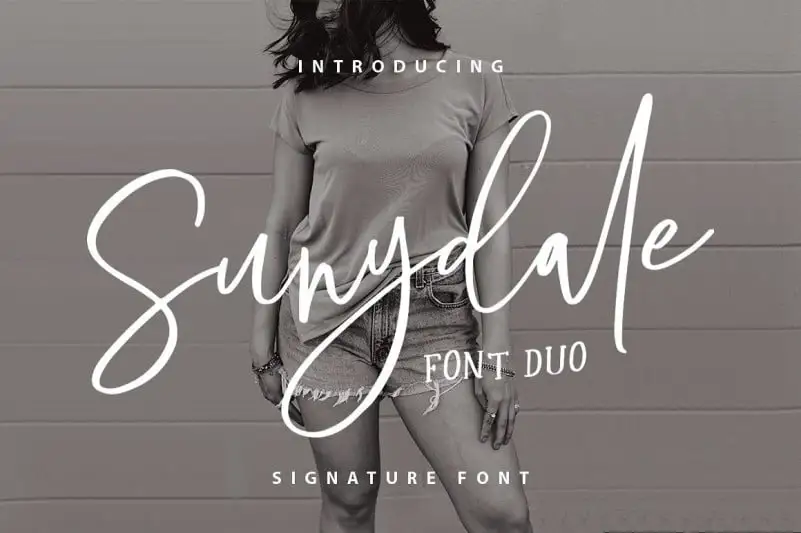
Descubra a elegância sofisticada que Sunydale traz à sua tipografia com seu estilo script moderno e seus traços serifados perfeitamente harmonizados. Esse duo de fontes é uma escolha inteligente para qualquer negócio aspirando ao glamour, seja ele no mundo da moda ou em blogs de tendências. Com uma aparência livre e feminina, Sunydale convida a se expressar com estilo, fazendo do seu projeto um elemento irresistivelmente atrativo e elegante. Seja o próximo que opta por esse encanto singular para personalizar seus materiais digitais.